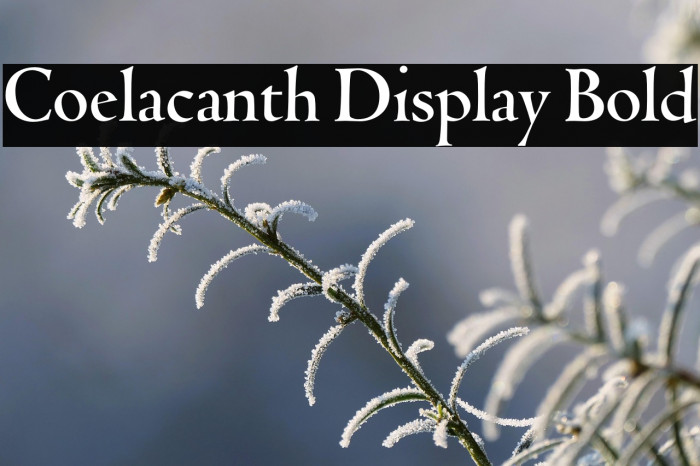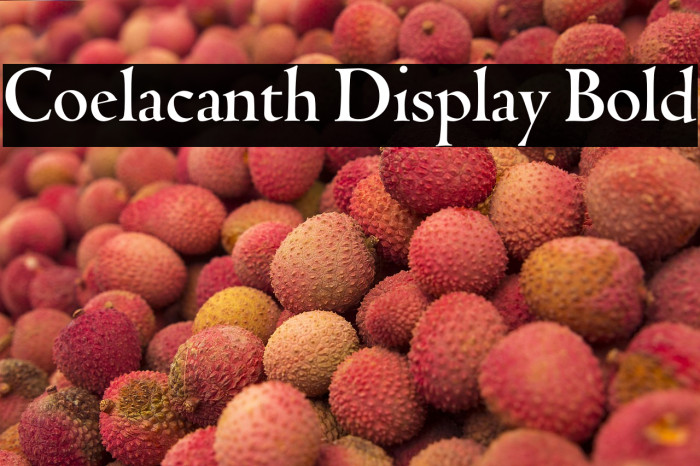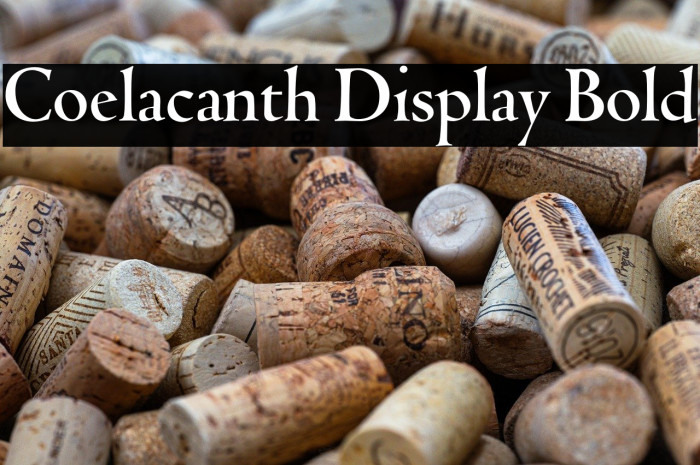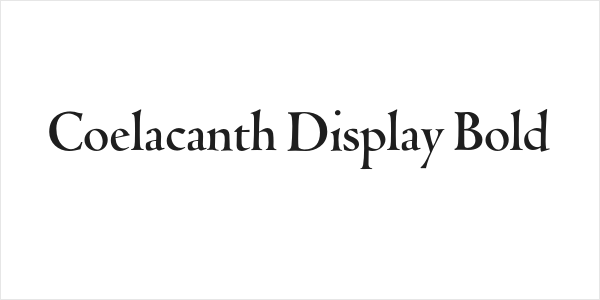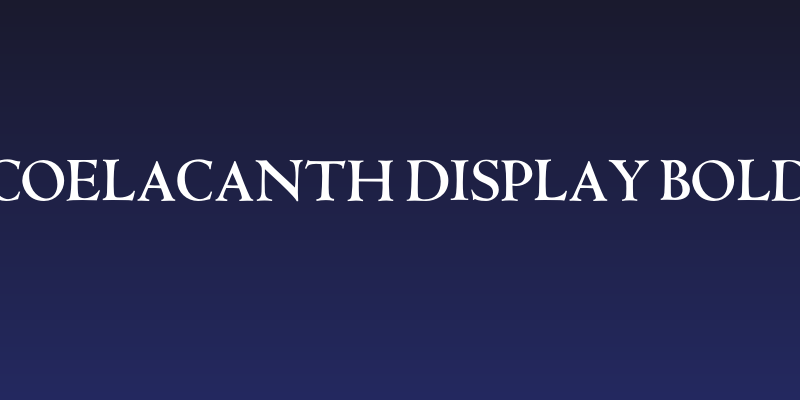
Coelacanth Display Bold Font
| श्रेणियाँ | Serif |
| कंट्रास्ट | High |
| समग्र शैली | Classic |
| उपयोग का मामला | Headlines, Logos, Posters |
| सुझाए गए प्रोजेक्ट | Ideal for use in headlines, book covers, posters, and branding projects that require a touch of elegance and drama. |